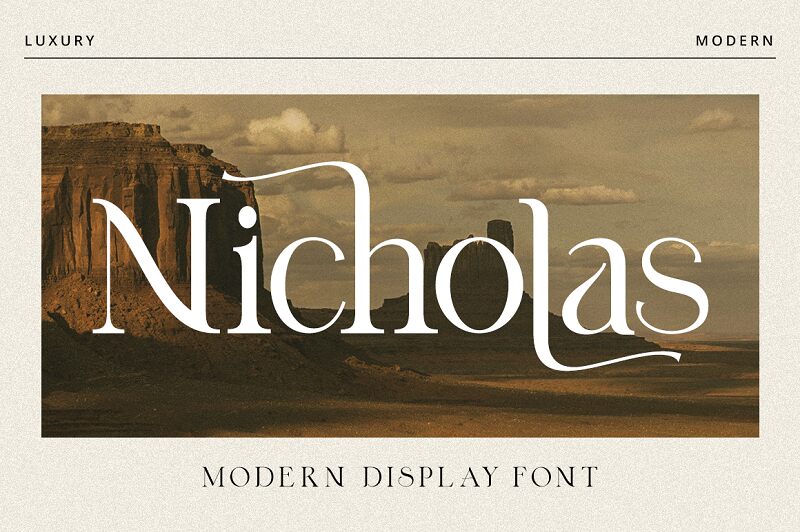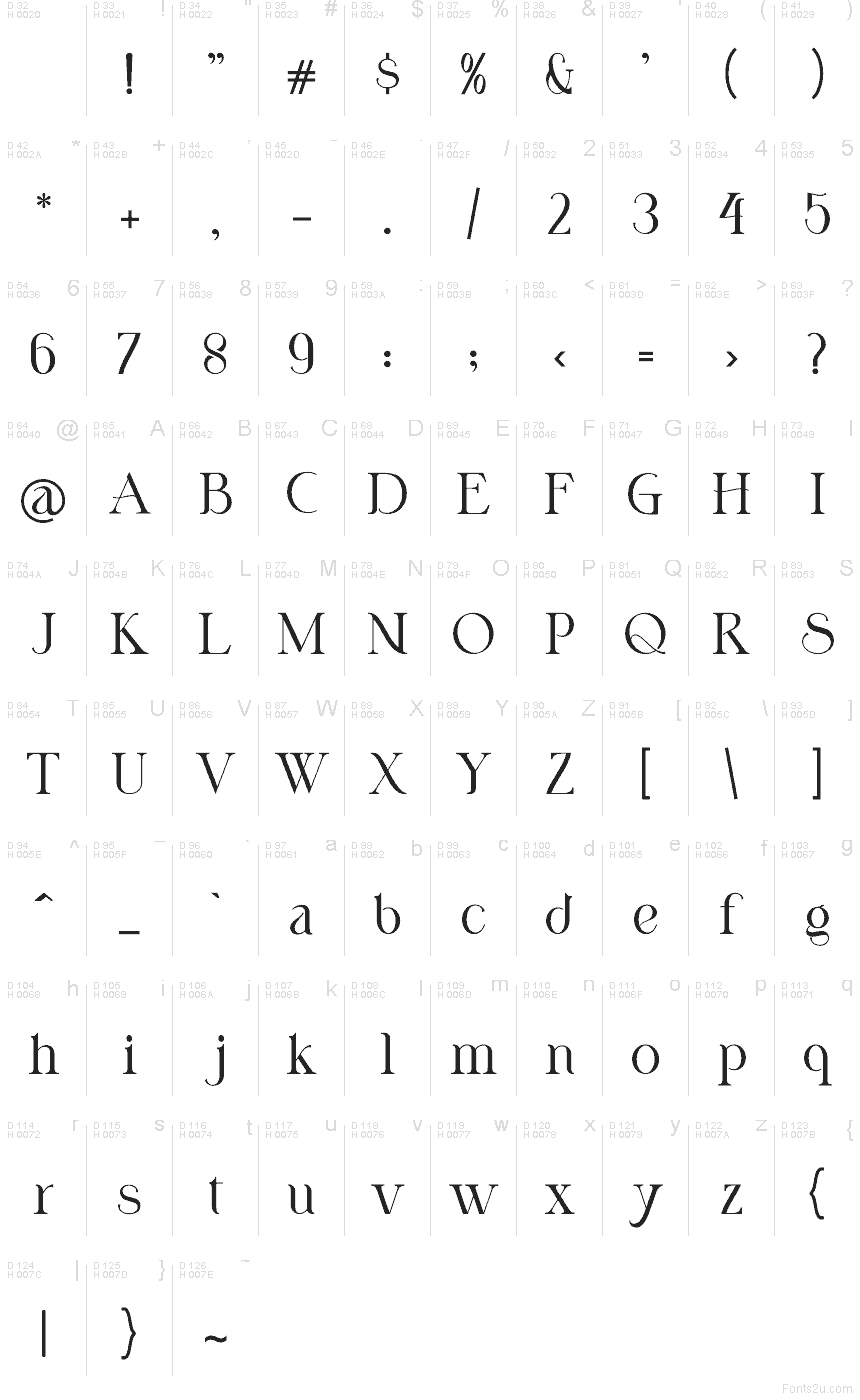
Nicholas Demo
Шрифт Nicholas от Hayinah из RockboyStudio — это бесплатная антиква с изысканным, книжным характером: четкие тонкие линии, уверенные жирные штрихи и гармоничные изгибы, которые придают ему премиальный вид без лишней вычурности. Текст выглядит как свежая печать на кремовой бумаге, а выверенный ритм делает даже длинные слова собранными и статусными.
Nicholas отлично смотрится в редакционных заголовках, брендинге бутиков, на обложках книг, в журнальной верстке, на приглашениях, в оформлении подкастов и упаковке продуктов. Этот бесплатный шрифт также эффектно выглядит в цитатах и hero-текстах на лендингах, если дать ему немного пространства. Для основного текста сочетайте его с лаконичным гротеском, используя Nicholas чуть крупнее, чтобы его тонкие детали оставались четкими.